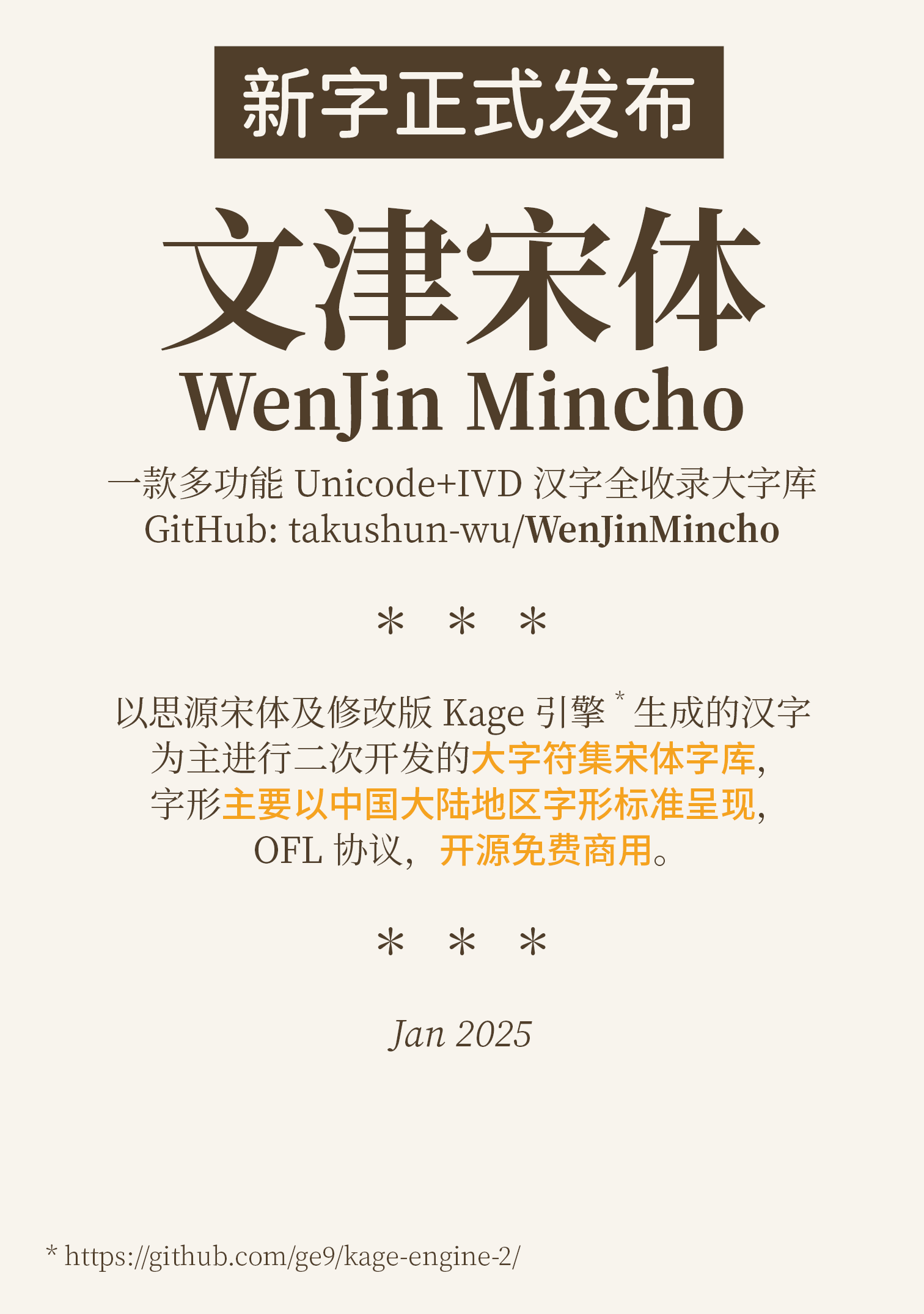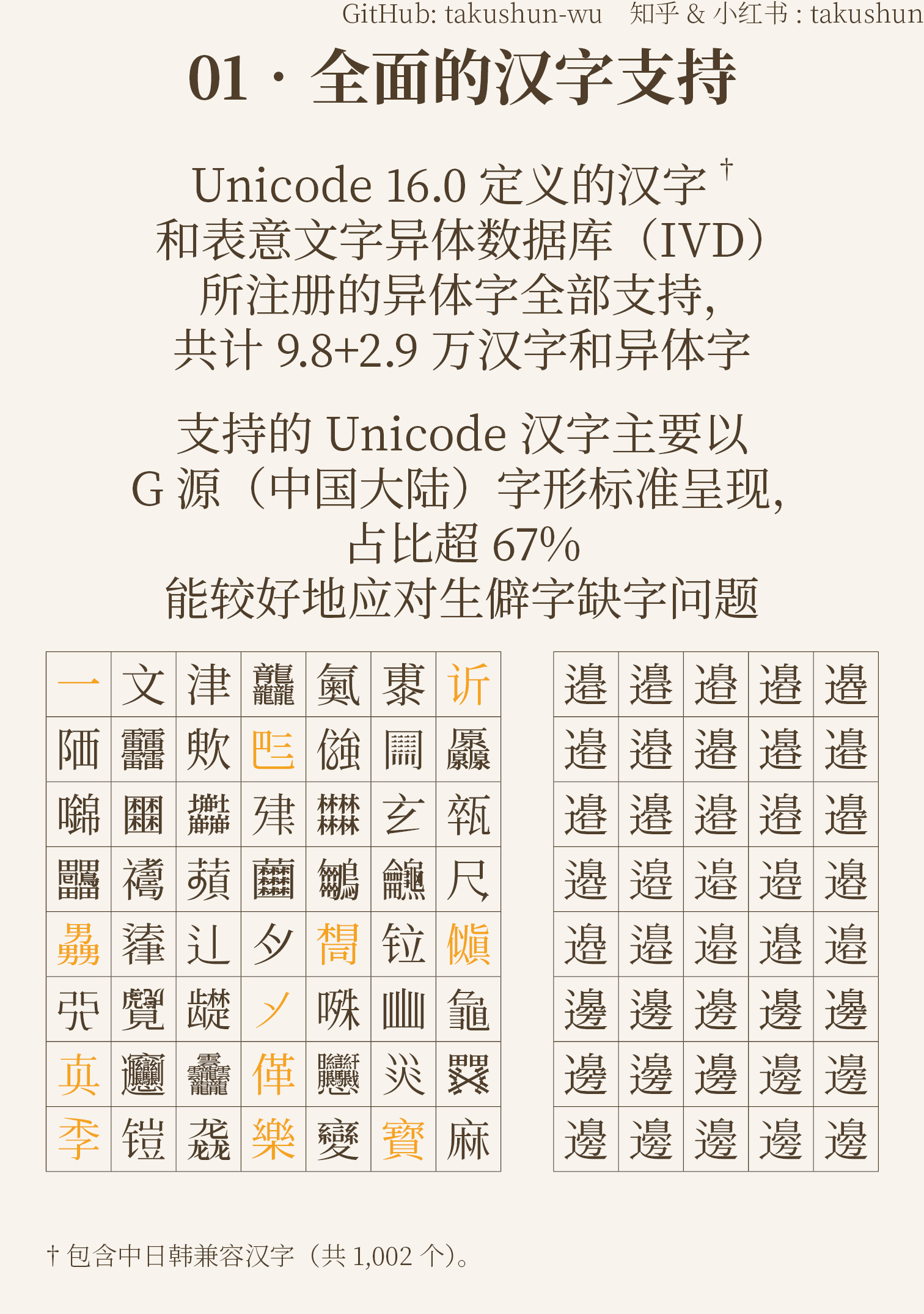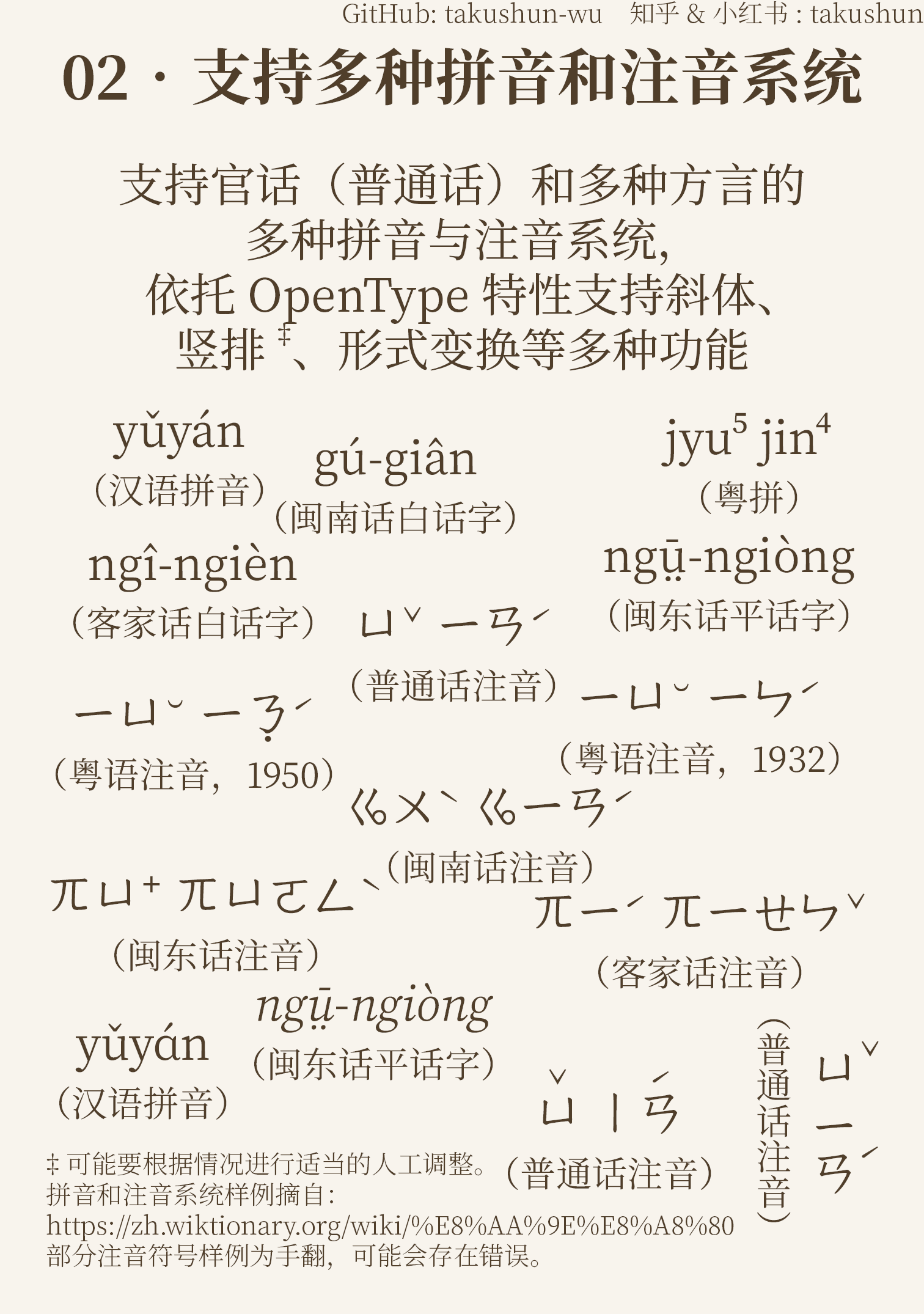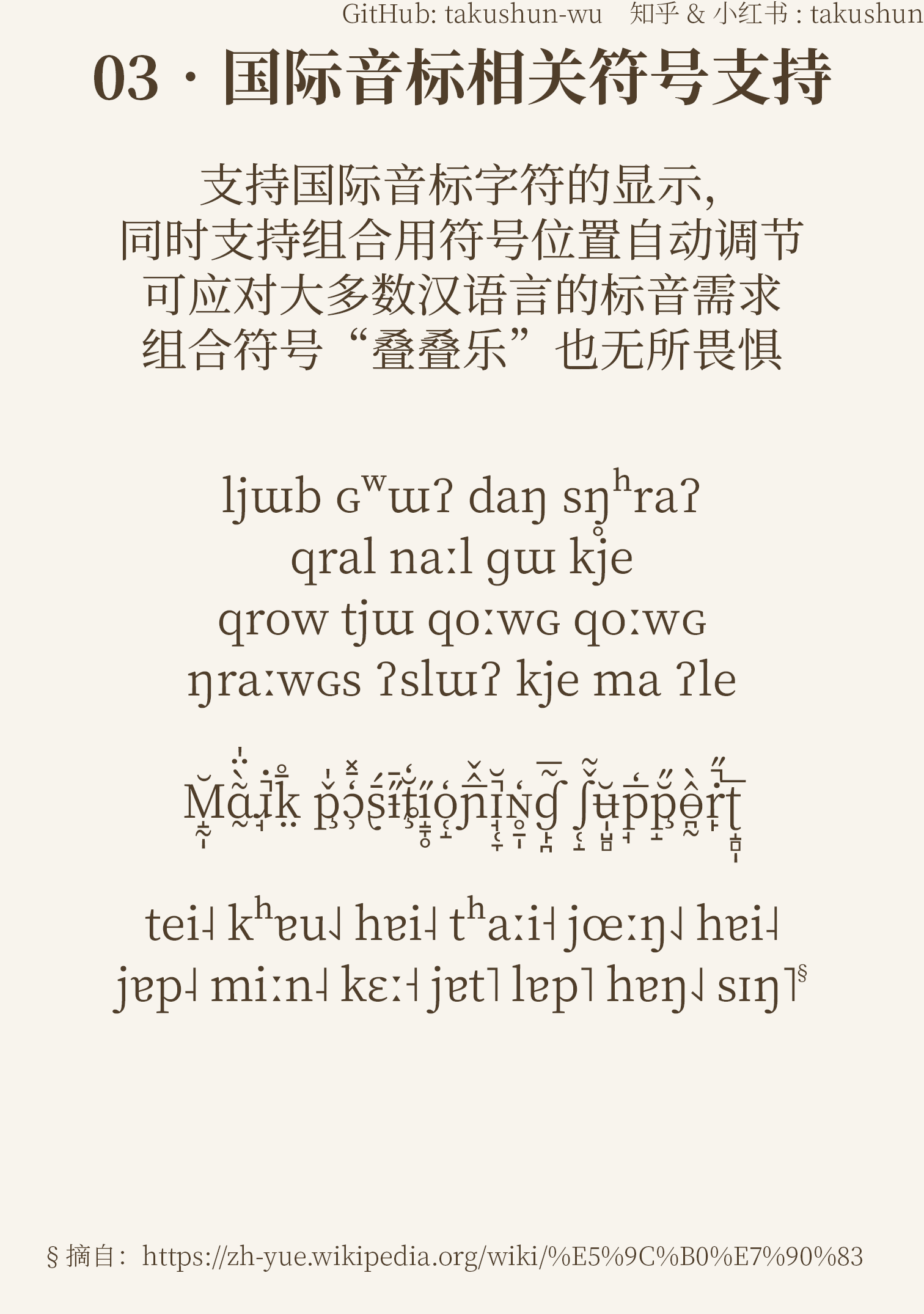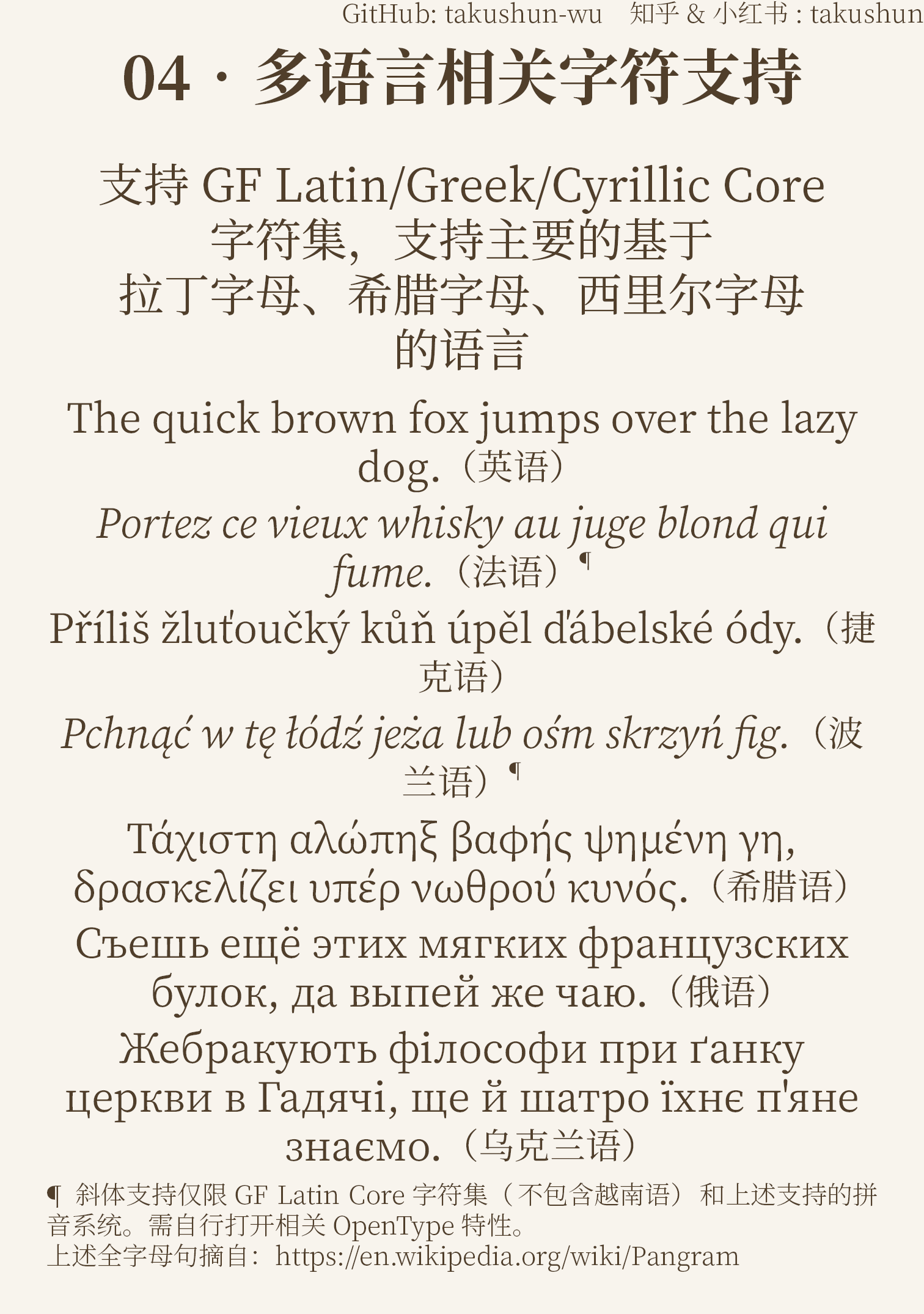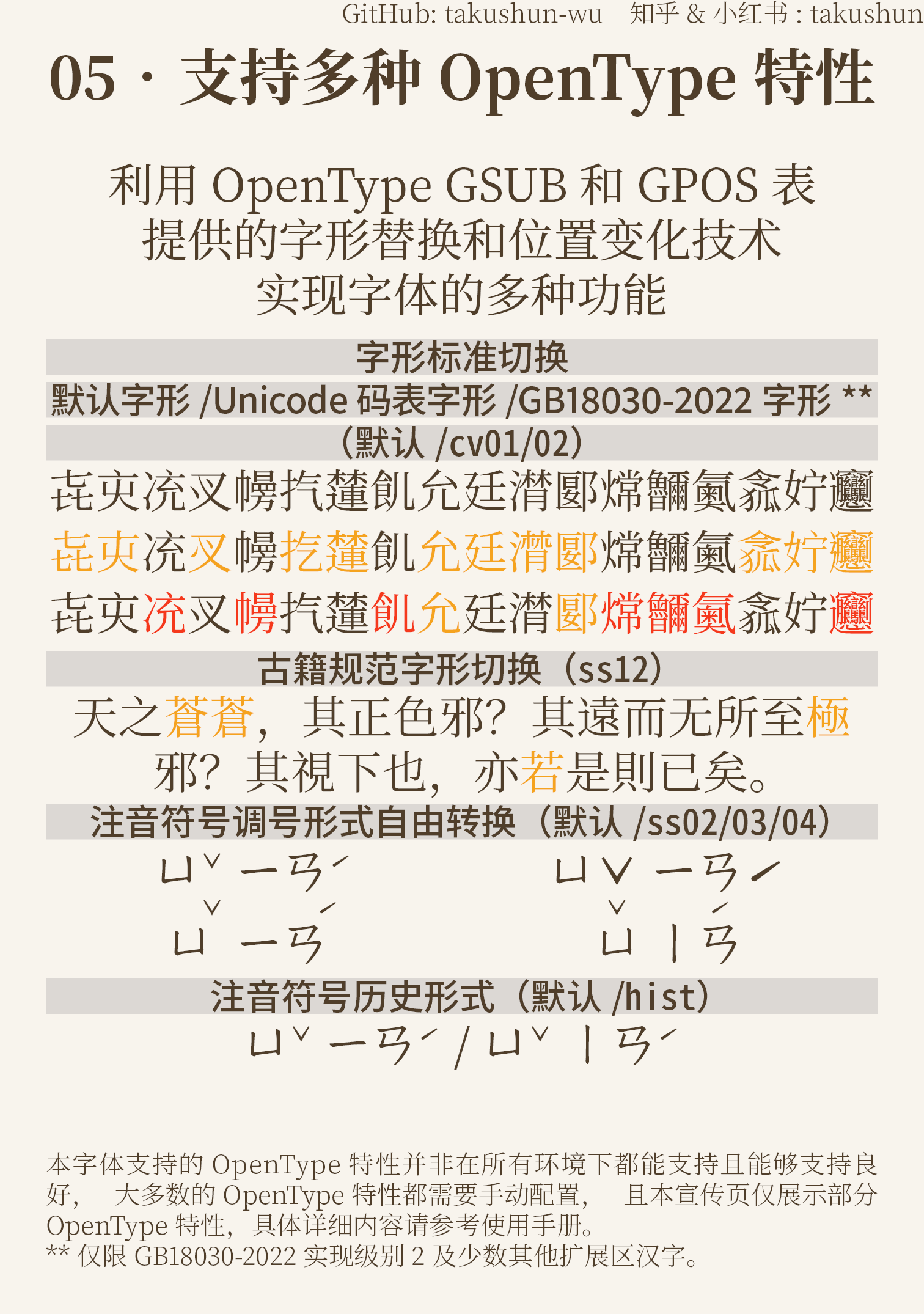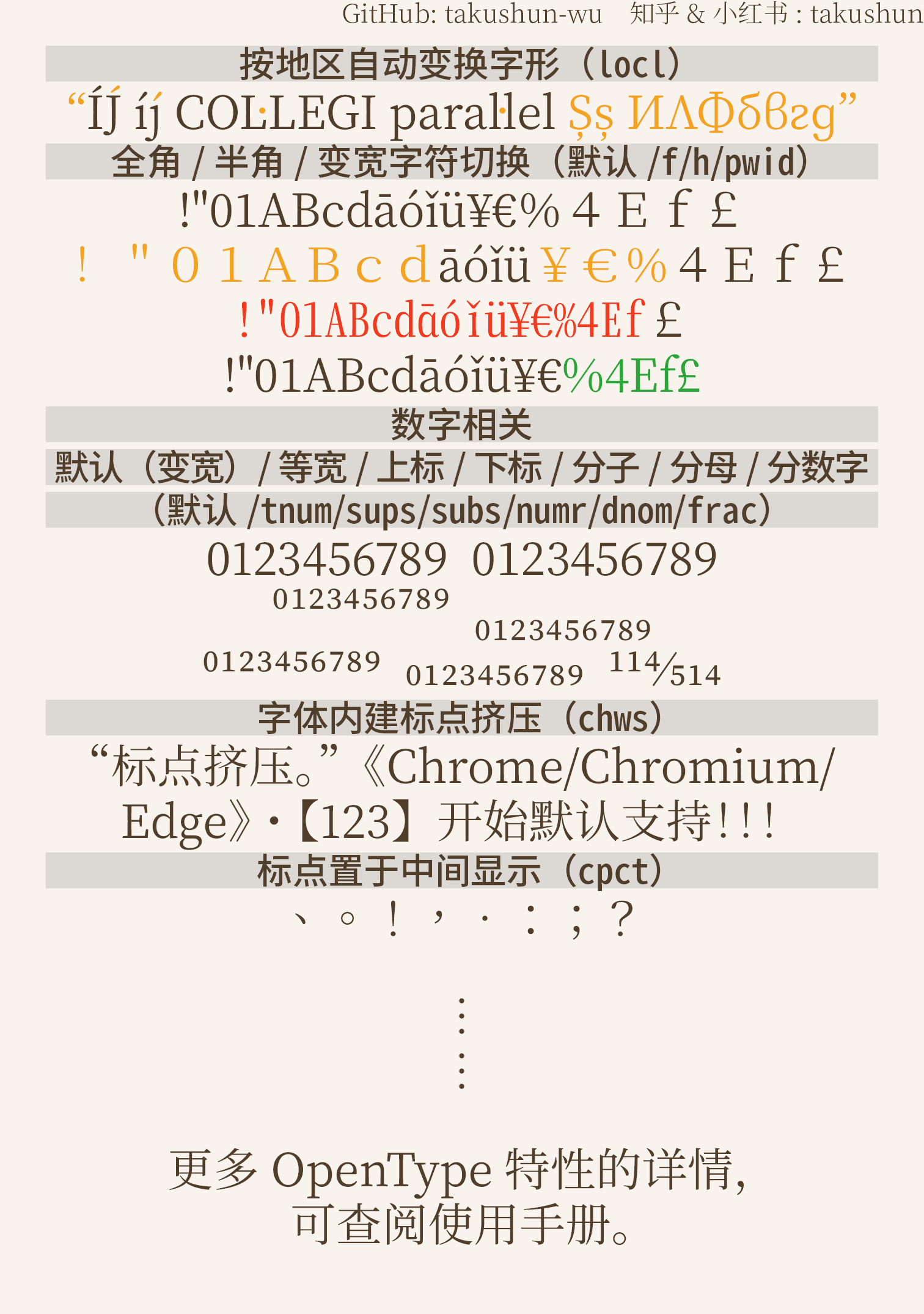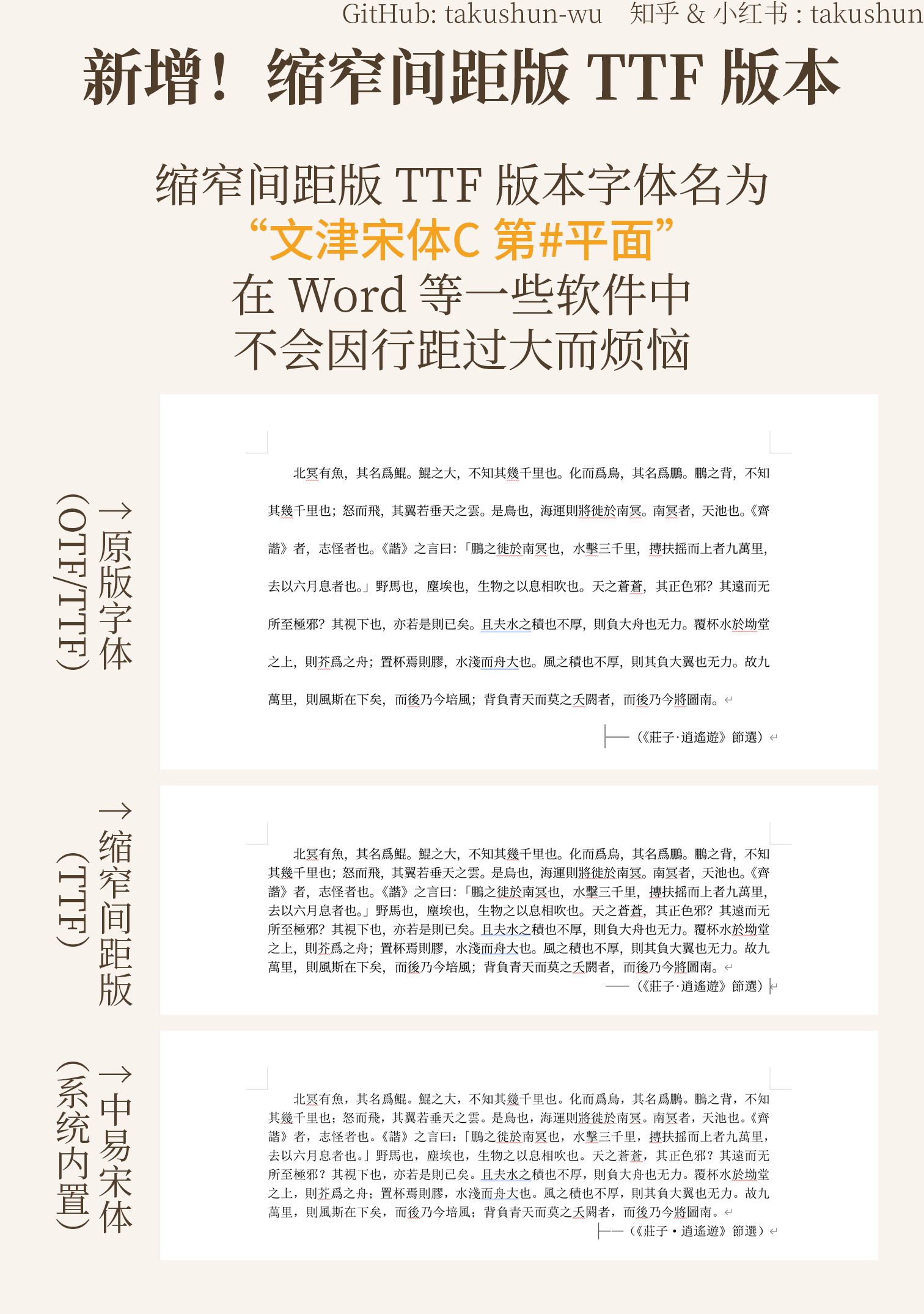
文津宋体是一套基于思源宋体及其衍生版本进行深度二次开发的大字符集宋体字体套装。它充分利用了GlyphWiki开源字形数据库以及经过优化的Kage字体生成引擎,从而实现了对Unicode标准中定义的全部汉字,以及表意文字异体数据库(IVD)中所注册字形的全面覆盖。该字体在呈现上尤其注重符合中国大陆地区的官方字形标准,确保在常用与生僻字形上的一致性与规范性。
除了广阔的字符覆盖,文津宋体还具备丰富的功能特性。它全面支持多种汉语拼音及注音符号系统,能够满足语言学习、出版标注等多样化需求。字体内部嵌入了多种OpenType高级特性,允许用户在支持的软件中自由调用,例如:可以方便地在不同字形标准(如中国大陆标准与台湾地区标准)之间进行切换;提供对拼音与注音符号变体形式的完整支持;实现了注音符号在传统竖排版式下的正确布局;确保了带声调标字符能够准确定位在元音字母上方;并内置了智能的标点压缩(标点挤压)功能,以优化中西文混排及连续标点时的版面效果。这些细致入微的设计,使得文津宋体不仅是一个字符齐全的“字库”,更是一个功能完备、注重排版质量的专业字体解决方案。
适配Unicode 18.0版本
- 新增扩展D区1个汉字
U+2B81E“”(⿰日欠); - 跟随G(中国大陆)源汉字横向扩展,178个汉字字形修改成G源(详细内容请点击此处);
- 126个汉字跟随其他源横扩或Unicode升级而修改字形(详细内容请点击此处);
- 新增中日韩笔画的VS1, VS2
U+FE00, FE01异体选择器的支持。
其他更新内容
新增内容
- 新增两个横向倾斜的大于/小于等于号:⩽⩾
改进与问题修复
- 从此版本起,缩窄间距版(C版)恢复更新;
- 将以下4个UTC源汉字修改至其他源:𠼻𢇆𪷼𭏒;
- 修正6个汉字:㾩*𦘝𩌦𪙒𬗜𮉪*(*为仅码表字形);
- 改进11个汉字:𣢣𤎋𤎑𤤘𥾲𥿽𦁁𦃀𦄠𫅮𦬖;
- BMP内全部、部分扩展B-J区、MSARG异体字集全部汉字与文渊宋体v1.100同步;
- 重制1,390个SAT源和1个UTC源(加粗)汉字(详细内容请点击此处)。
新增内容
- 新增日本文字情报基盘整备事业(Moji_Joho)7个IVD异体字,详情请见此处。
- 新增以下9个非汉字符号:⁺⁻₊₋⚠←↑→↓
- 新增1/3、1/4、1/6em宽、数字宽度、极细(1/8em宽度)、纤细(1/16em宽度)空格;
- 新增〝〞〟的竖排形式。
改进与问题修复
- 修正26个汉字(为默认及GB/T 22321.1-2025字形,†为仅码表及GB/T 22321.1-2025字形);
- 优化4个汉字。